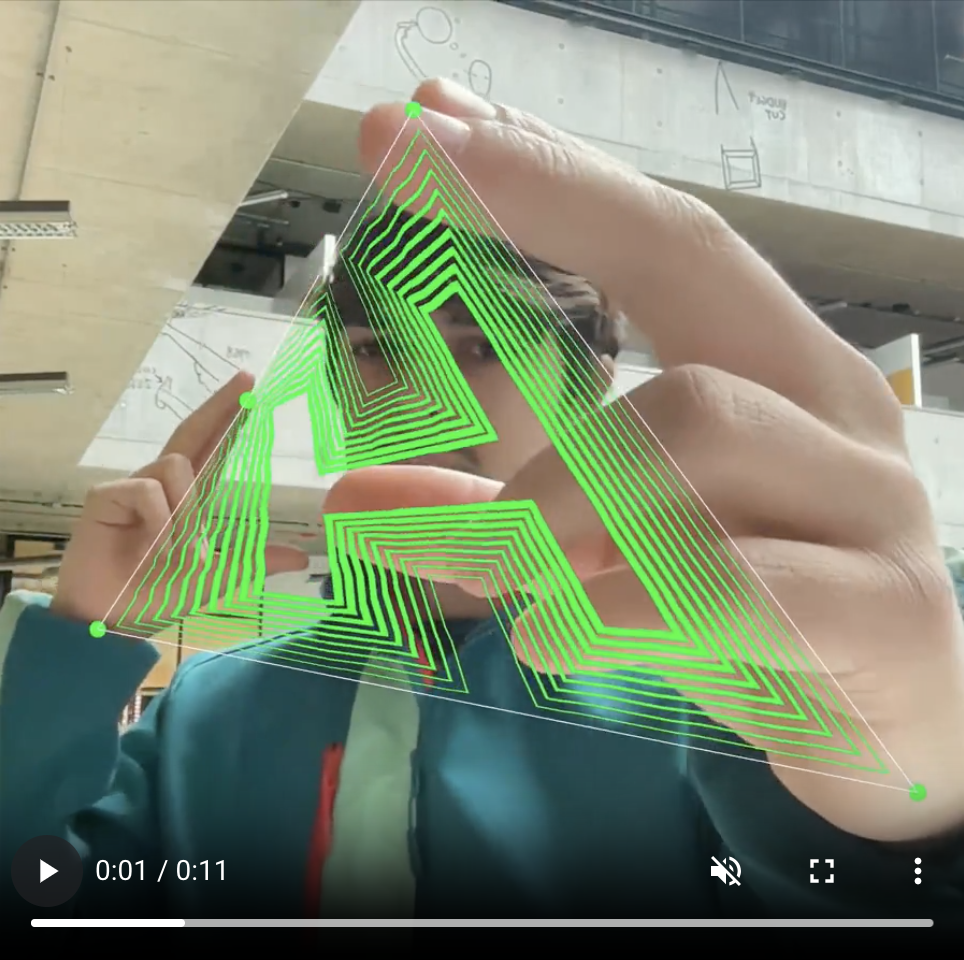
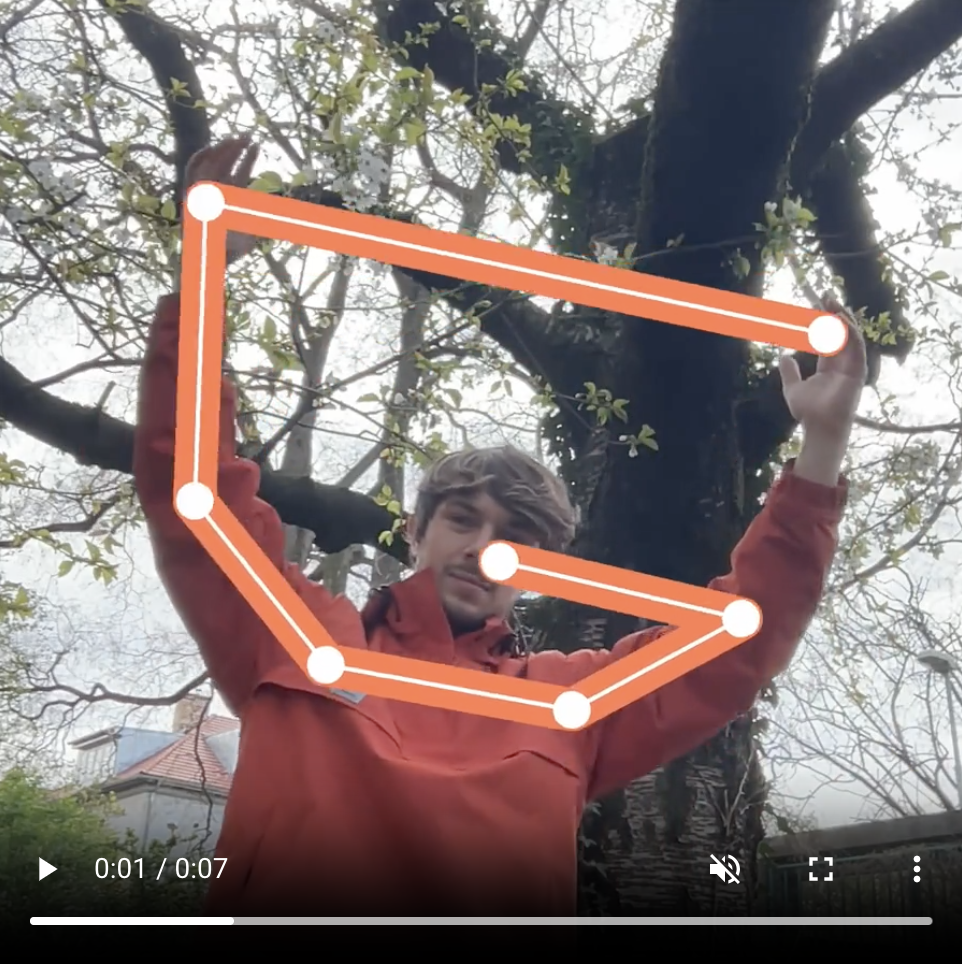
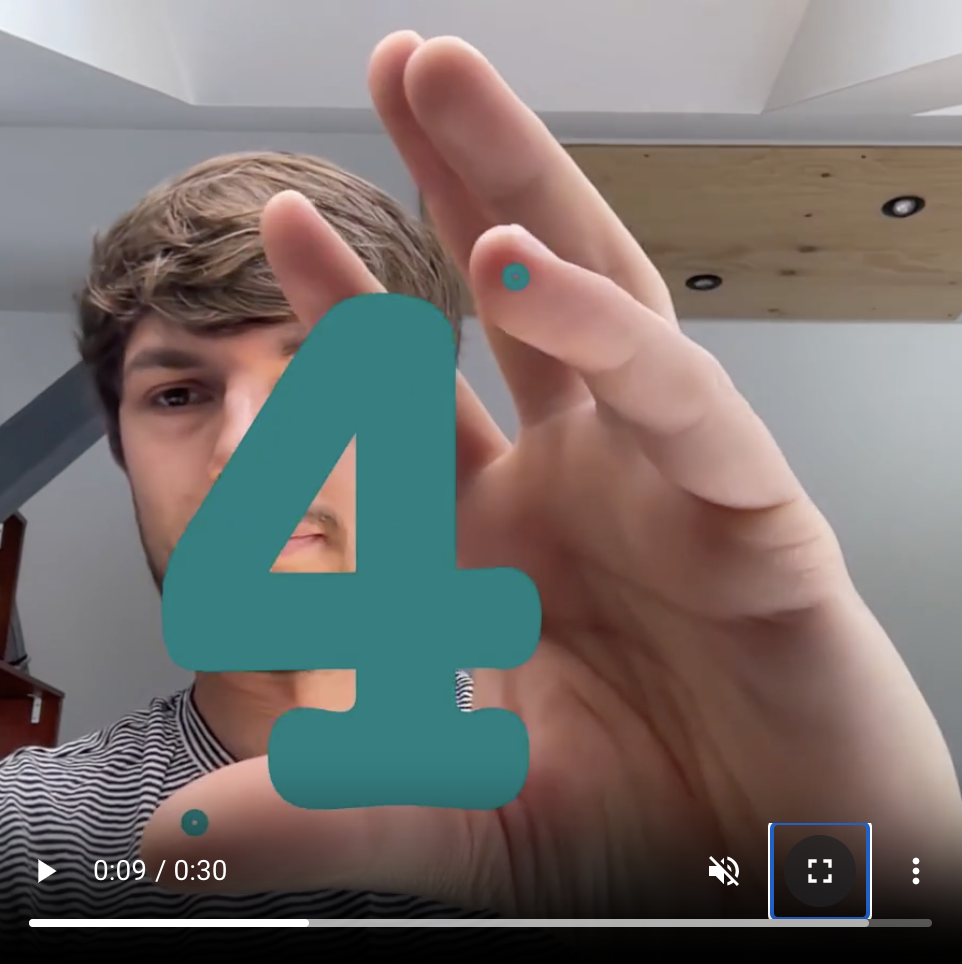
Relevancia en relación a la tipografía interactiva
Este proyecto es una colección de 36 experimentos tipográficos desarrollados para el reto "36 Days of Type". El sistema utiliza un algoritmo de machine learning (Mediapipe) y P5.js para detectar y rastrear partes del cuerpo del usuario a través de una cámara web, usando esos datos como input para manipular las formas de los glifos.
Su principal aportación es la materialización del concepto de ‘interacción corporeizada’ (embodied interaction). A diferencia de otros sistemas, aquí la interfaz convencional desaparece y son los gestos del usuario la herramienta para generar y transformar los caracteres.
La relevancia de este proyecto es que demuestra un modelo de interacción alternativo a los periféricos tradicionales como el ratón o el teclado. Al establecer una conexión más directa e intuitiva entre el gesto y la expresión visual del texto, abre nuevas vías para explorar la expresividad en la tipografía interactiva.
Clasificación
- Función: Exploración formal y/o performativa
- Contexto: Investigación / Experimental
- Grado de interactividad: Interactivo
- Tipo de input: Gestual
- Tipo de output: Transformación morfológica
- Tecnología empleada: P5.js, Machine Learning (Mediapipe)
- Alfanumérica: Sí
- Mantiene codificación textual: No